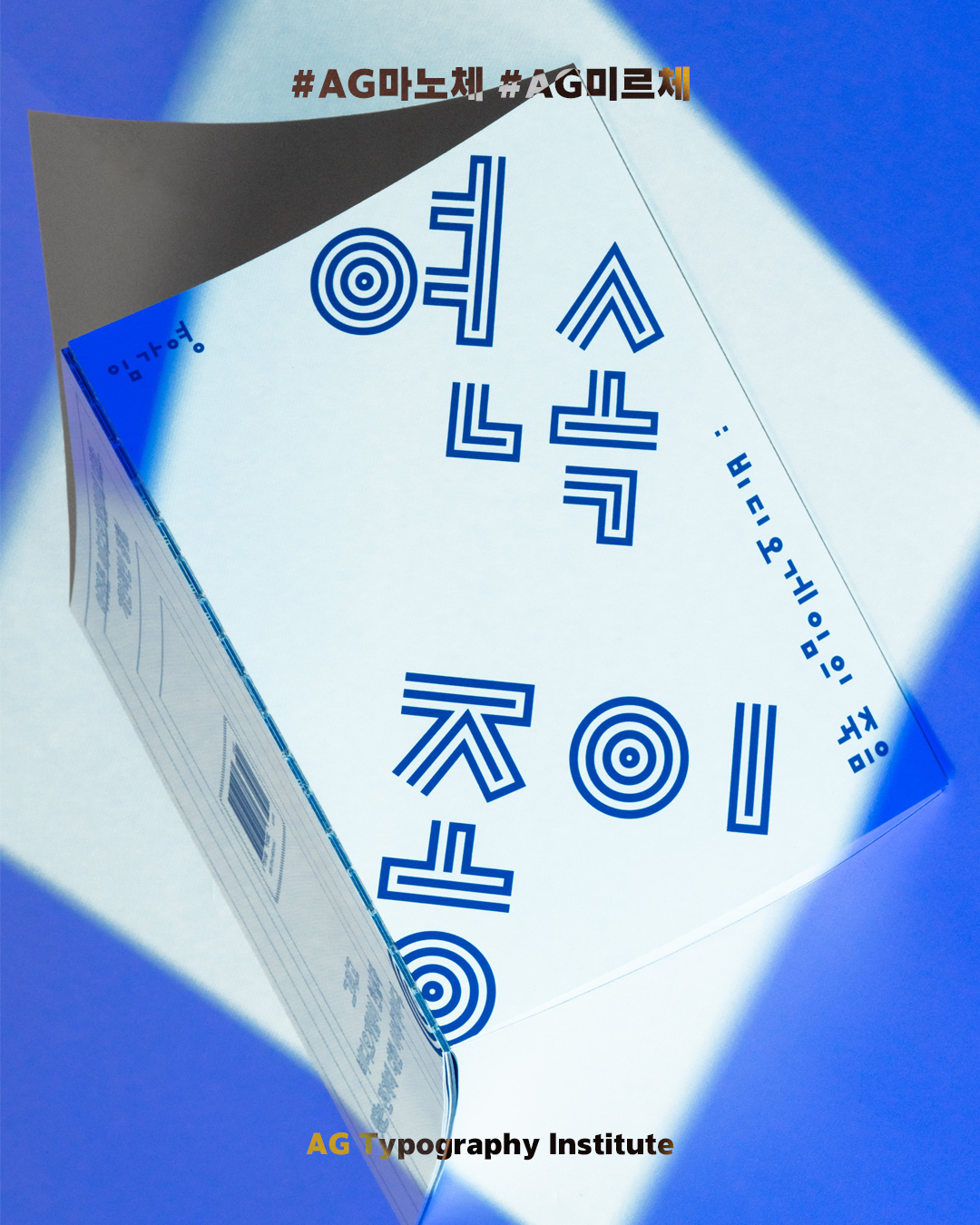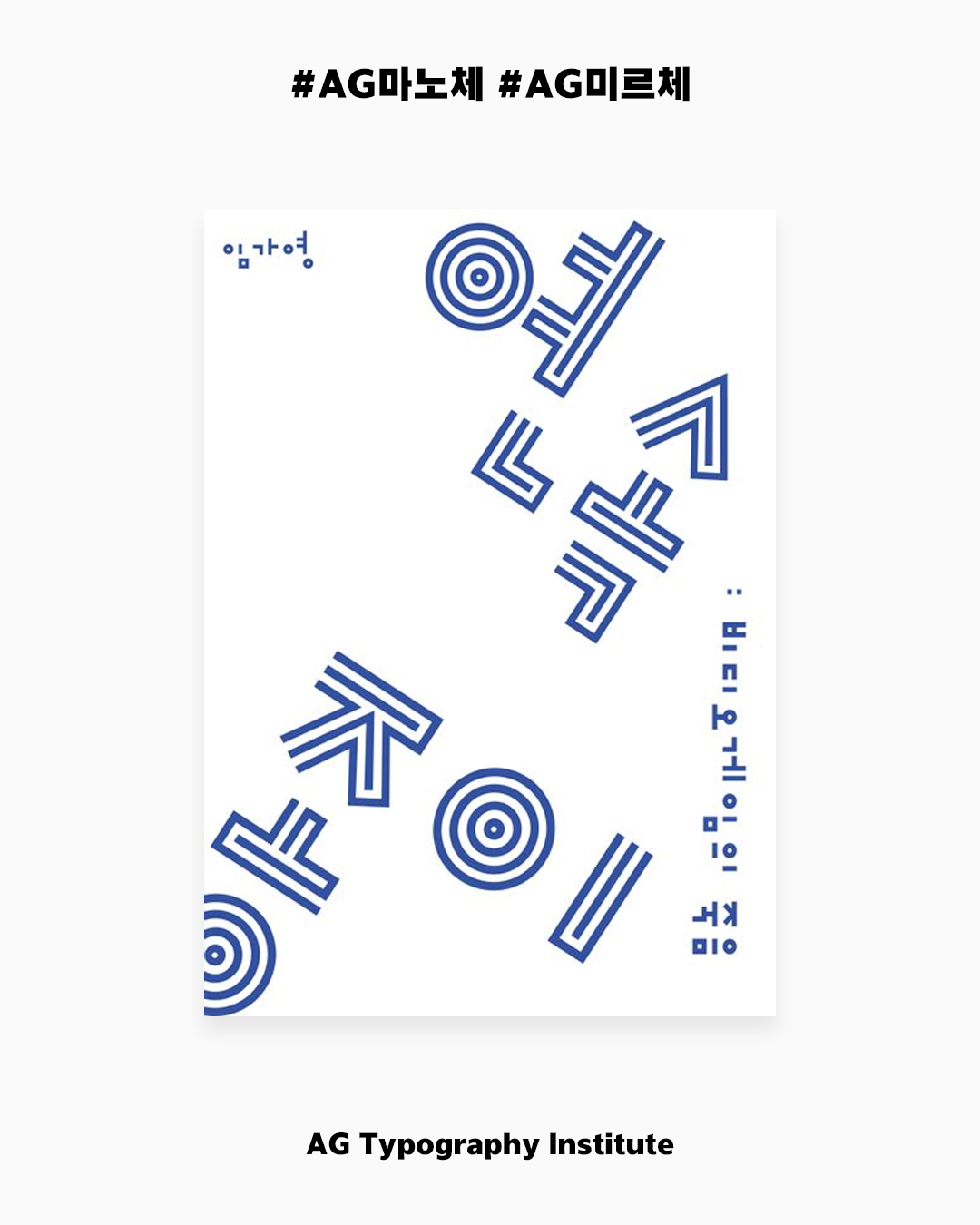
AG 마노체 2014 패밀리
AG Mano 2014 Family
〈마노체〉는 1993년에 첫선을 보였다. 안상수체 이후 세벌식 모듈 글꼴에 대한 다양한 실험이 이루어졌고, 그 중 〈마노체〉는 선 모듈로 이루어진 글꼴이다. 〈AG 마노체 2014〉는 디자이너 안상수가 설계한 〈마노체 2013〉을 판올림 한 것이다. 2007년 1차 판올림이 진행되어 3종의 굵기 파생이 이루어졌고, 2014년 2차 판올림으로 5종의 굵기 파생과 함께 한글, 라틴, 숫자, 기호 활자의 시각 보정이 이루어져 다벌식 탈네모틀 글꼴로 재구성했다.